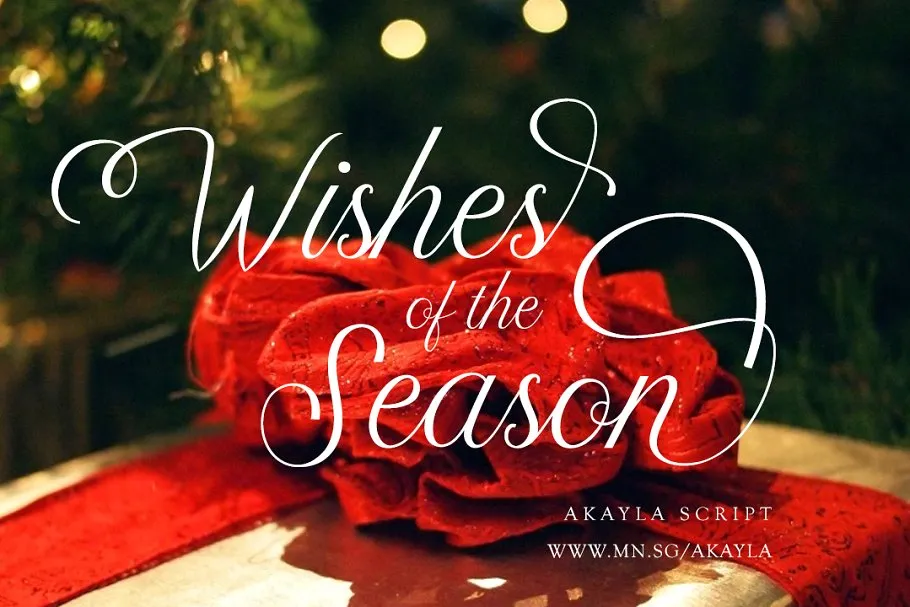
Akayla Script Font é uma nova fonte de escritura artesanal, rica em emoção e estilo romântico. Inspirada na chamada, esta fonte oferece um rico acervo de script para criar designs incrivelmente belos para casamentos. Akayla é uma tipografia genuína de escritura, com seus traços fluidos e detalhes cuidadosamente elaborados que contribuem para dar um toque pessoal aos projetos. Com alternativas estilísticas e de traços variadas, esta fonte apresenta uma grande variedade e oferece-se como uma escolha perfeita para o branding, cabeçalhos de mídia social, embalagens de produtos, convites e cartas de casamento. Perfect para qualquer projeto que deseje dar um toque único e elegante, Akayla Script Font é uma excelente adição a sua coleção de fontes digitais.